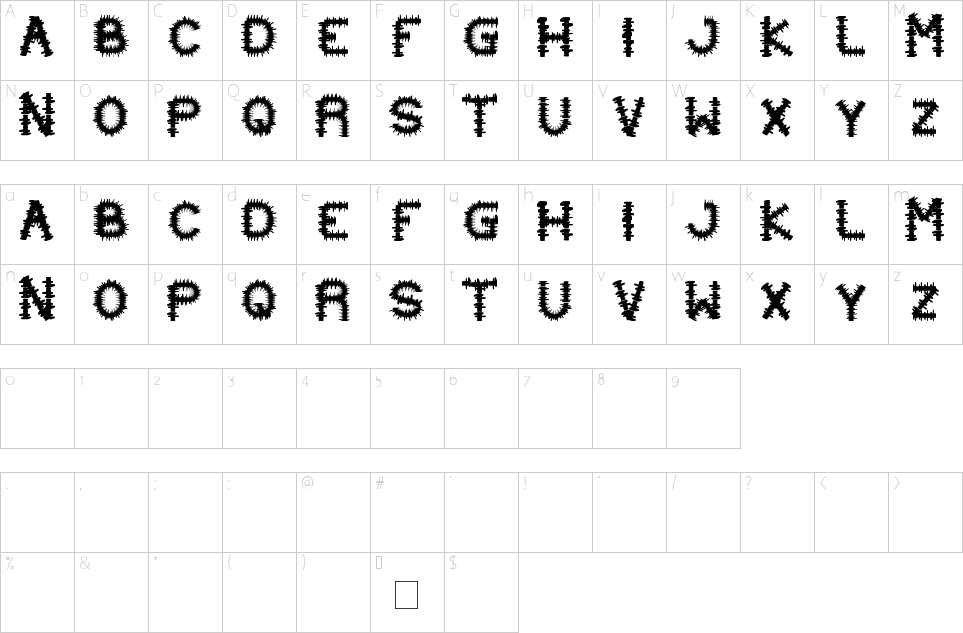
Descubra a fonte Punk em nossa coleção de 1001 Free Fonts, ideal para quem busca uma font que expressa estilo e modernidade. Através do designer descontraído e ousado conhecido como weknow, o Punk font surge como um ícone para designers gráficos. Este estilo punk atemporal enriquece qualquer projeto, seja um design de logotipo, um site ou até mesmo um cartão de visita. Recentemente, a fonte foi baixada 2.033 vezes, o que mostra o quanto ela é valorizada e popular. Se você está procurando por uma fonte que expressa sua personalidade e estilo de maneira única, Punk font é uma escolha sólida. Experimente ela e dê um toque inovador a seu design.